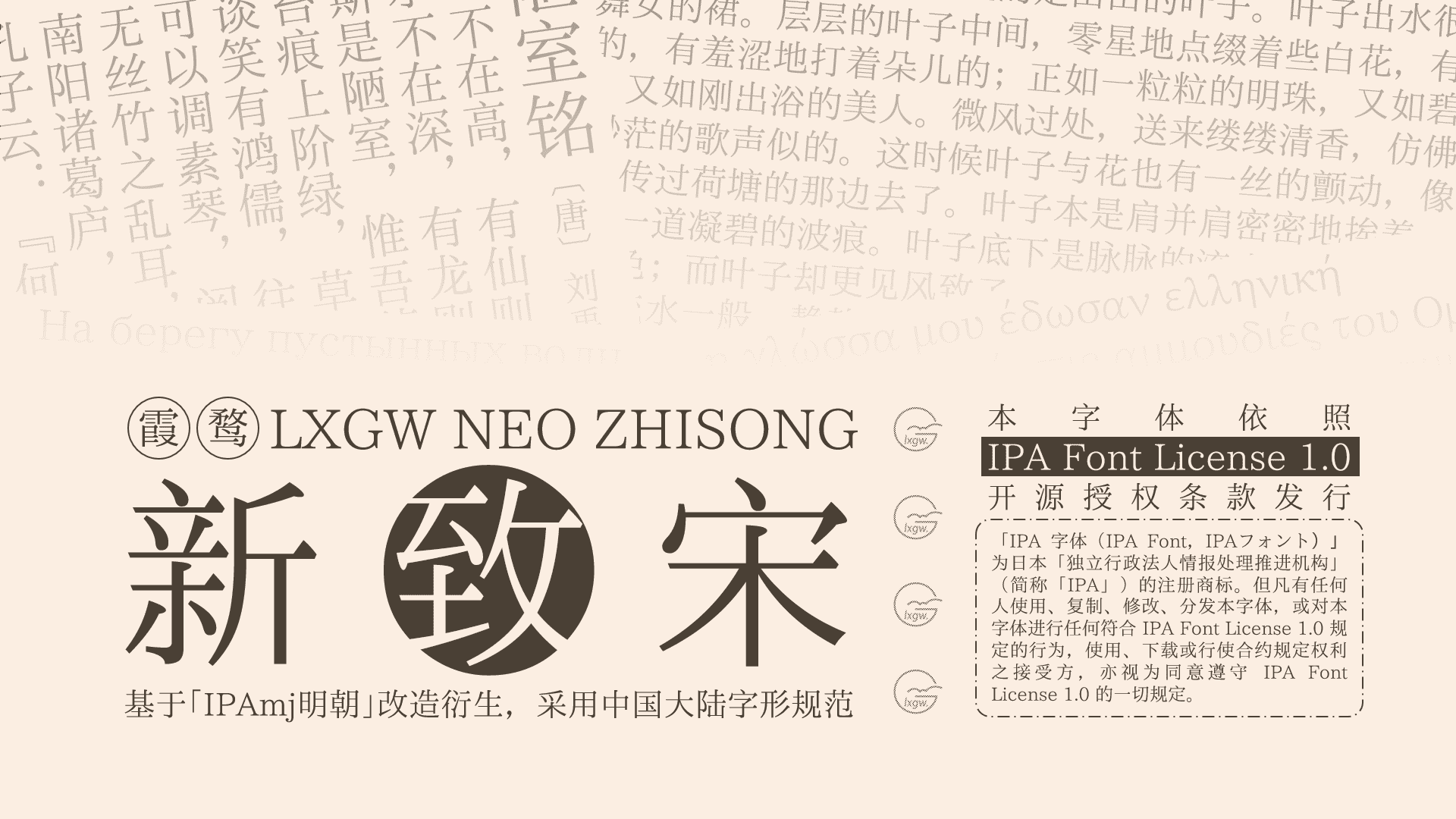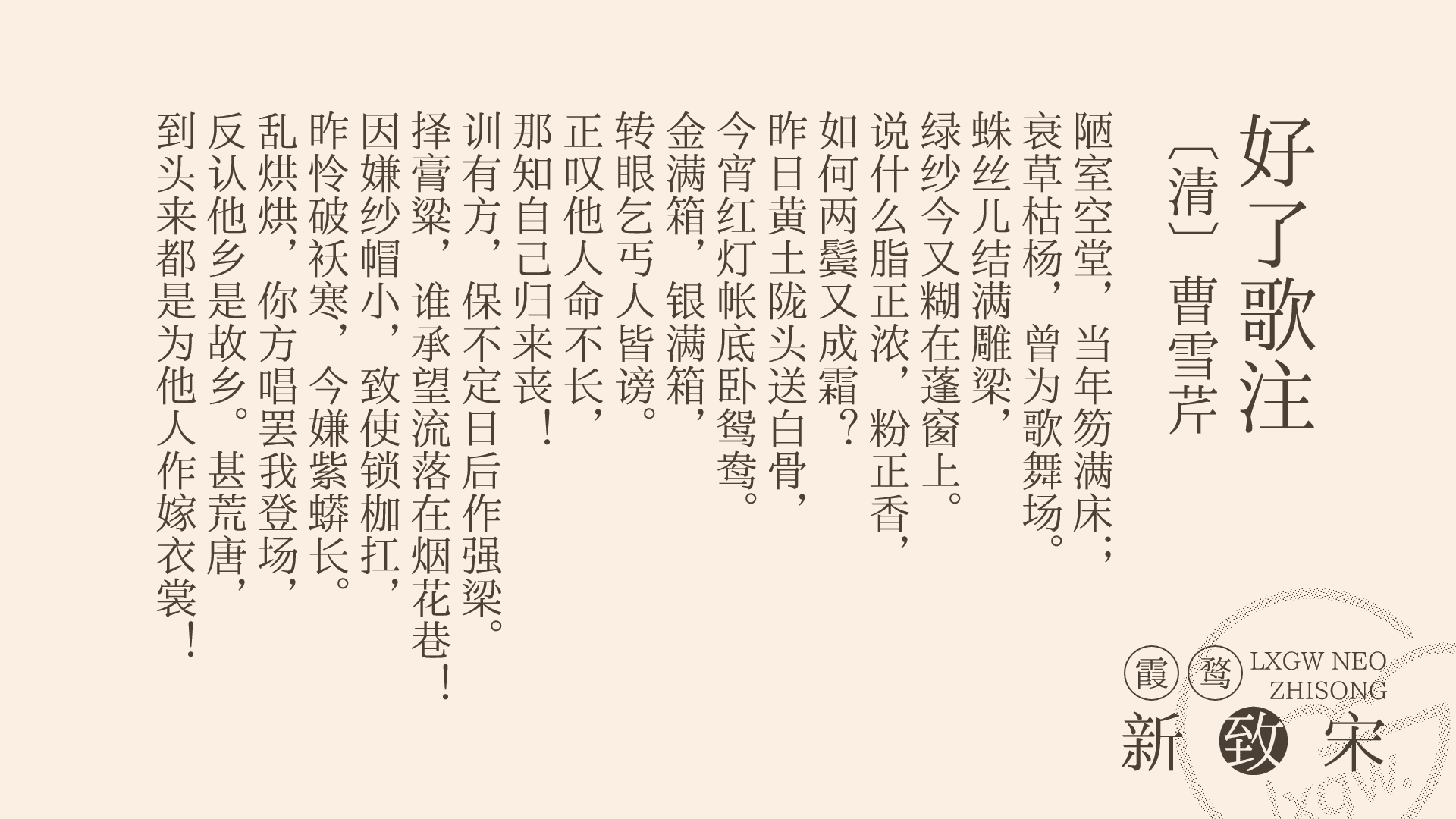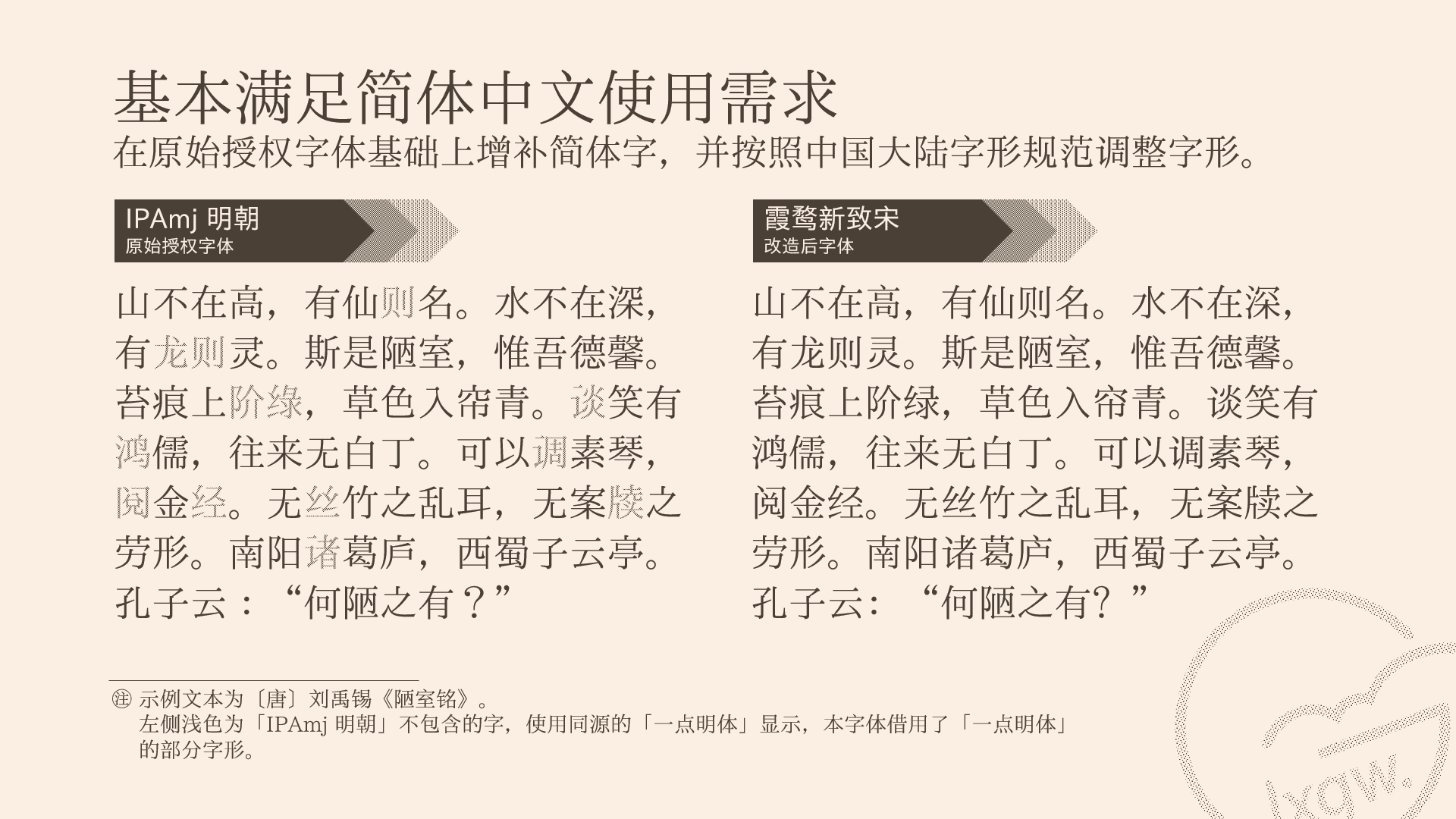
这是一款基于 IPAmj明朝 的中文开源字体,是将日本写法的字体改造成中国大陆规范写法的尝试。
本字体是「霞鹜新晰黑」的姊妹字体,尝试在「IPAmj明朝」原有字形的基础上,将其改造成中国大陆规范字形。
计划字汇
第一部分(简体为主)
现代汉语常用字表 3500 字;
GB/T 2312-1980 汉字部分 6763 字;(短期计划目标)
通用规范汉字表 8105 字;
现代汉语通用字表 7000 字;(中期计划目标)
此外按需添加一些表外字,共分为 5 组,详见外字初步整理表。(视情况而定)
第二部分(繁异体为主)
视情况而定。